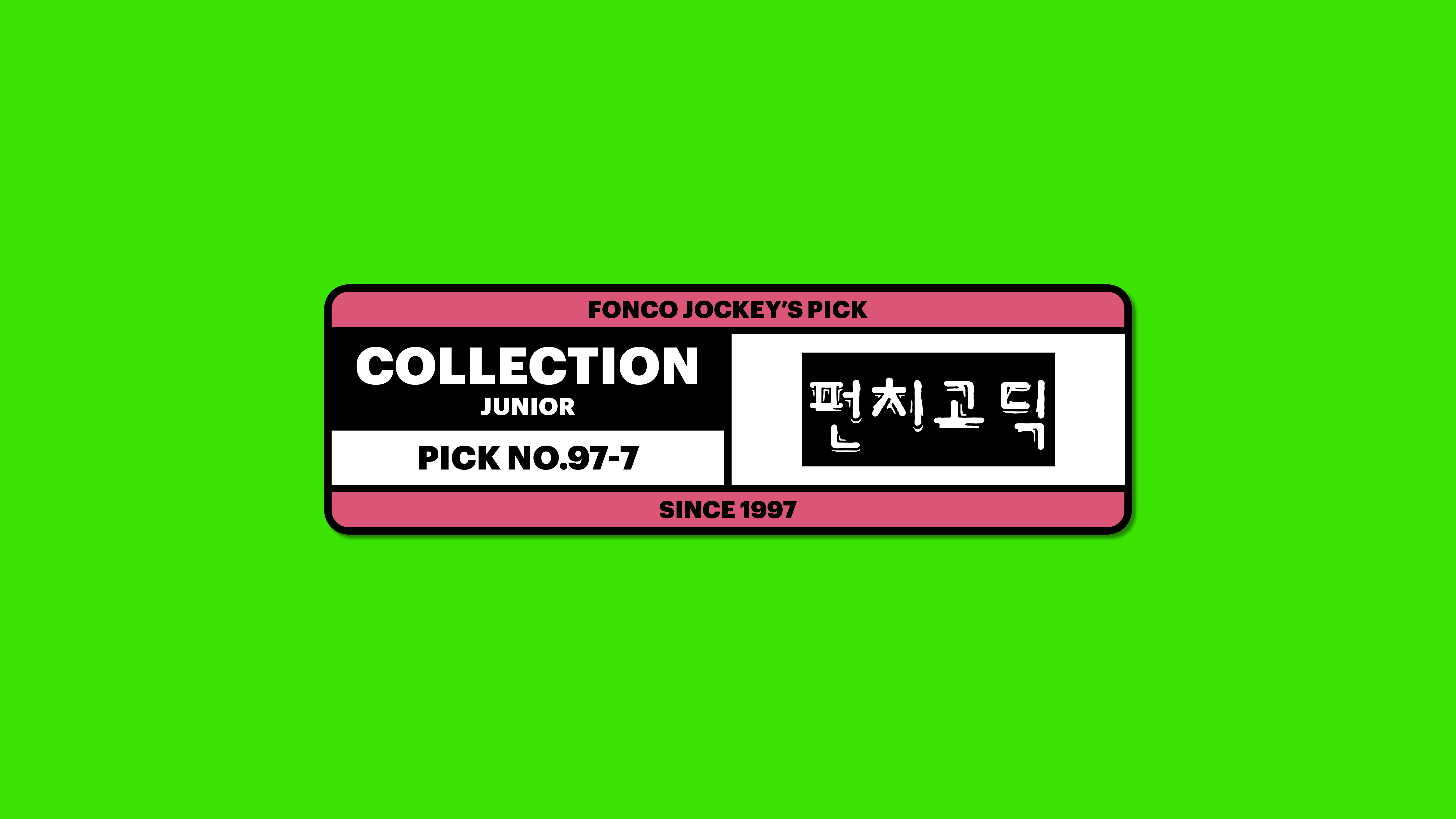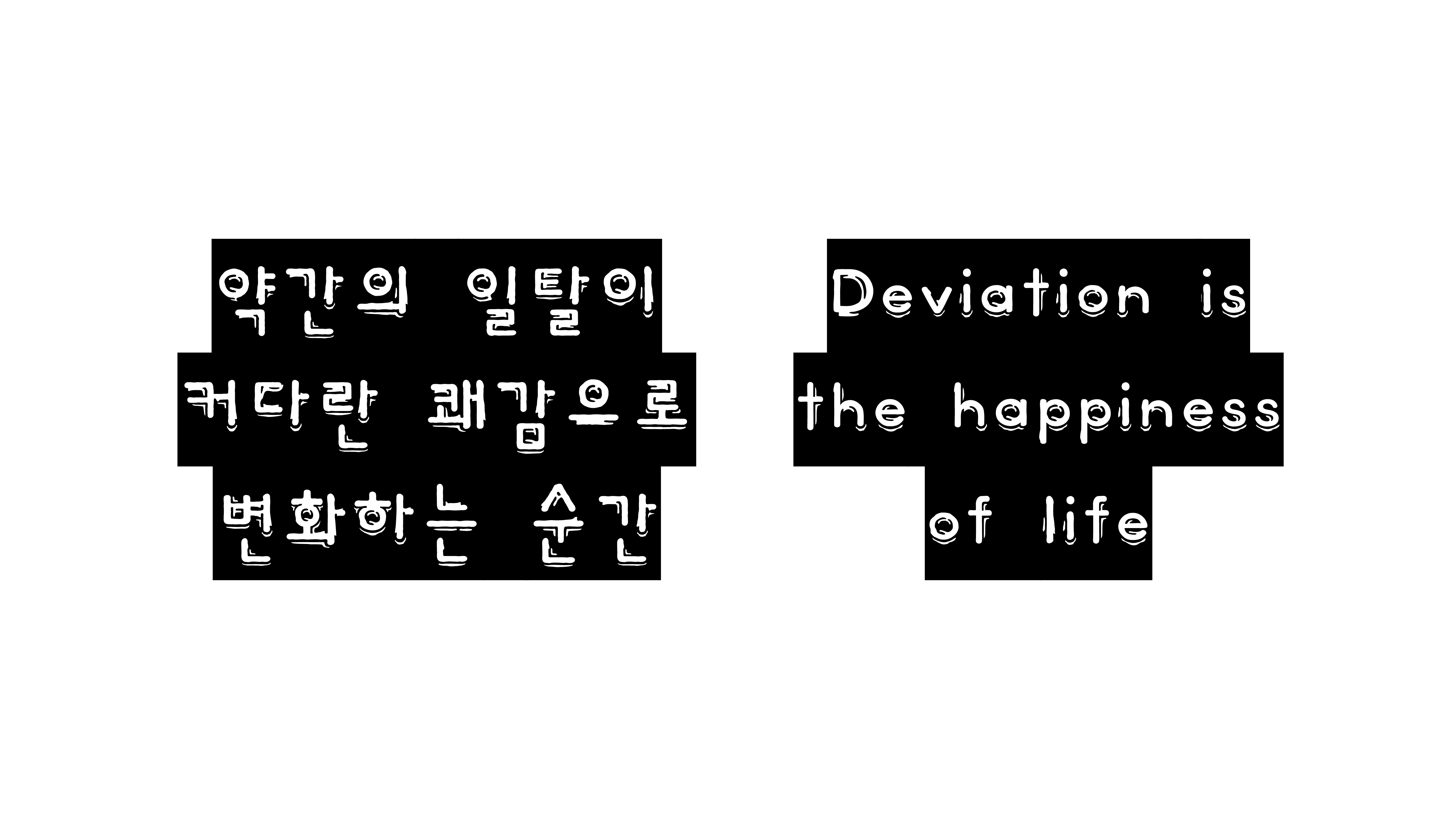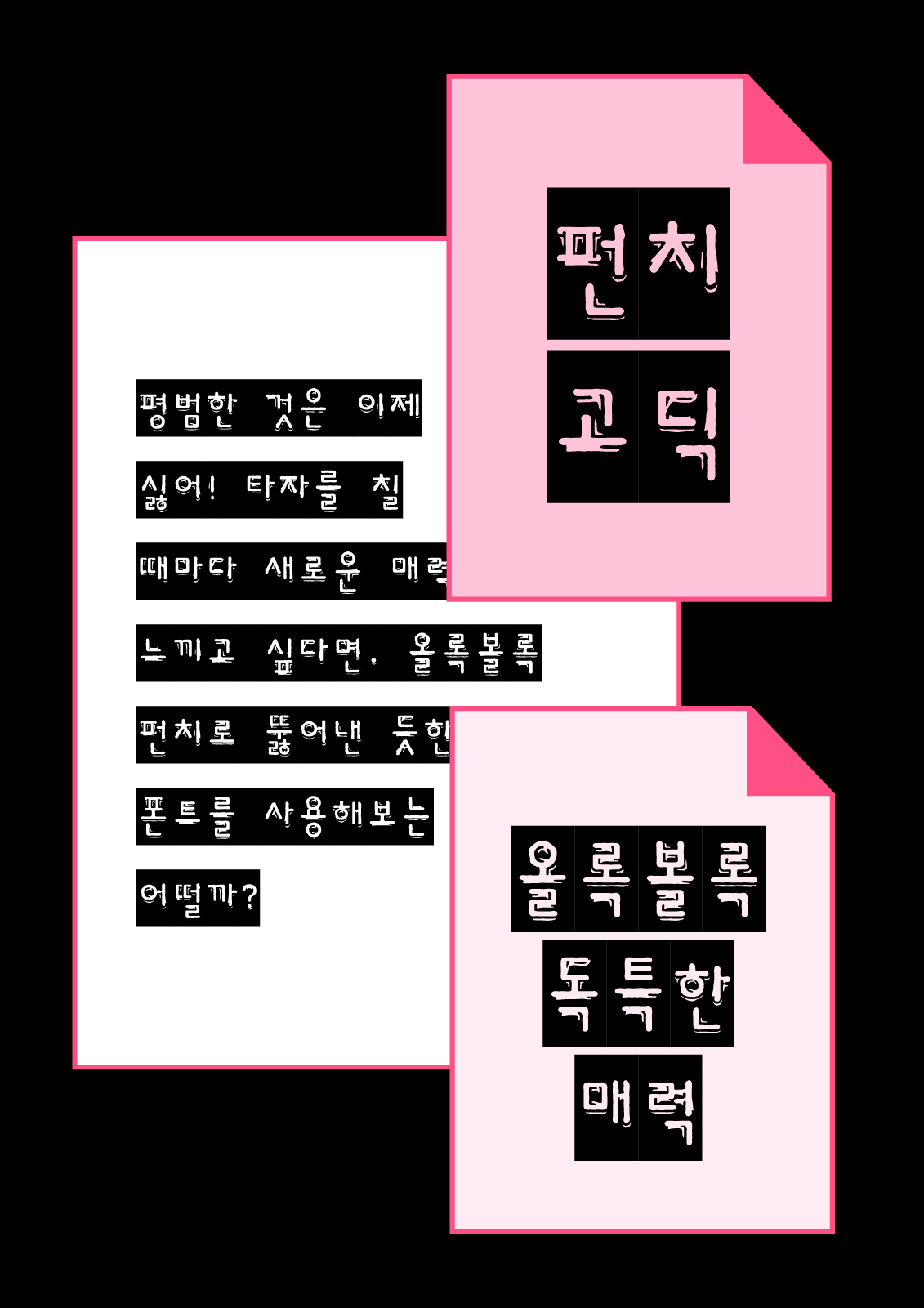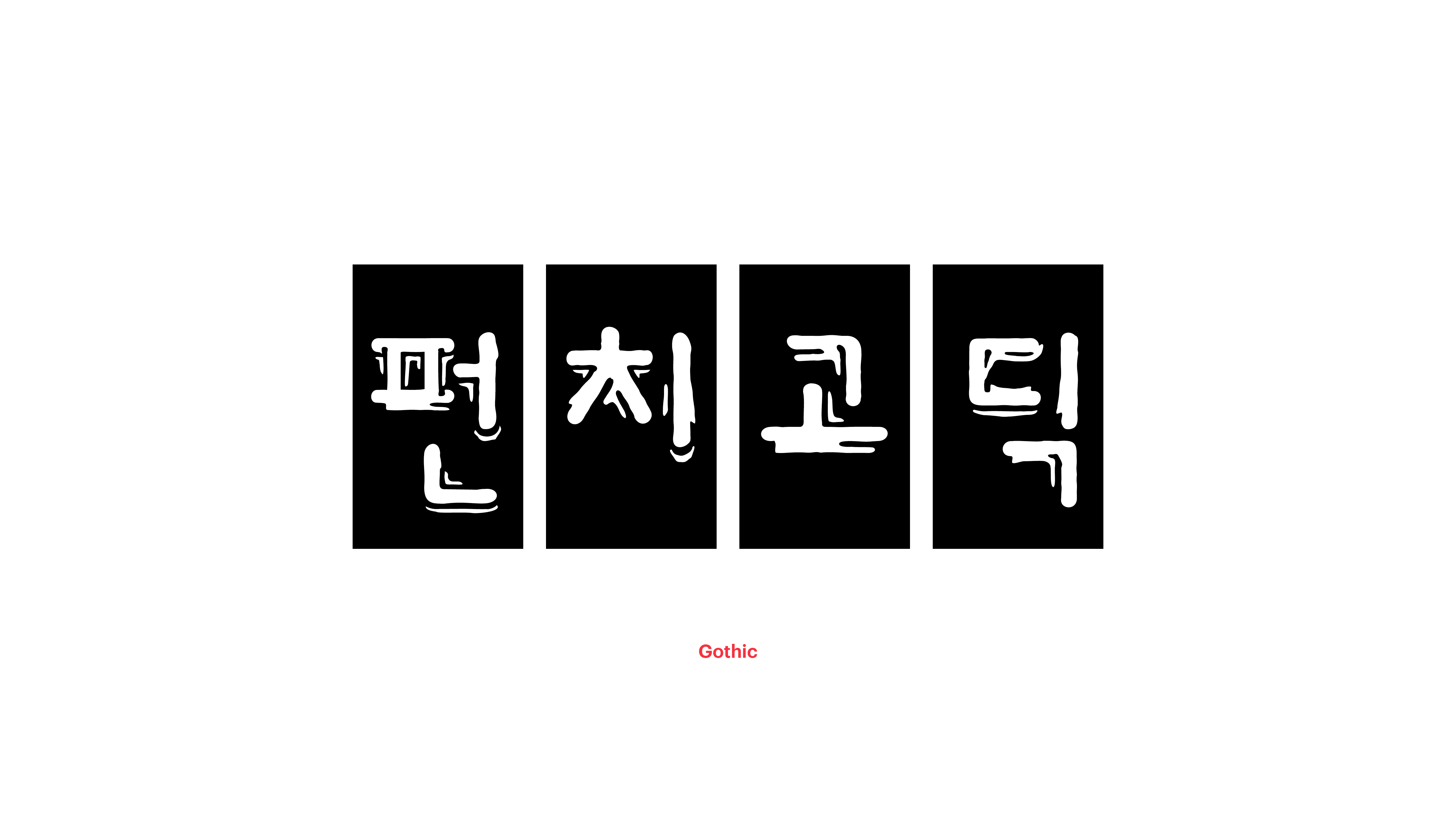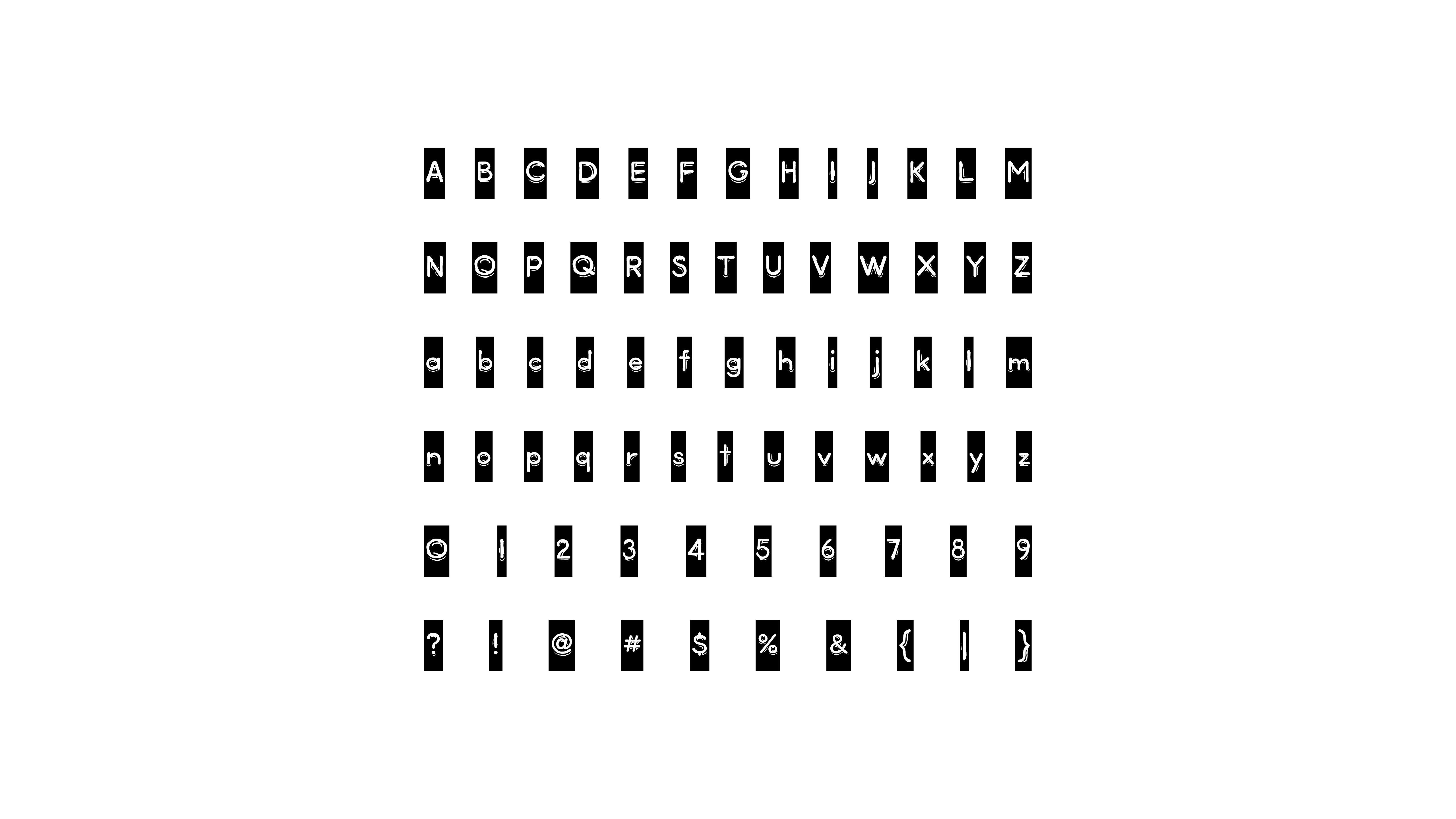
펀치
Yoon 펀치
약간의 일탈이 커다란 쾌감으로 변화하는 순간이 있습니다. 쓰면서 즐기는 폰트, 펀치체처럼 말이죠. 펀치고딕과 펀치명조로 구성된 펀치체는 펀치로 종이를 뚫어 글자를 새기듯, 글자 테두리에 마련된 음영 공간에 폰트를 새겨볼 수 있도록 디자인한 폰트입니다. 심심하고 지루하고 따분한 날, 펀치체와 함께 무료함을 싹 날려보세요!